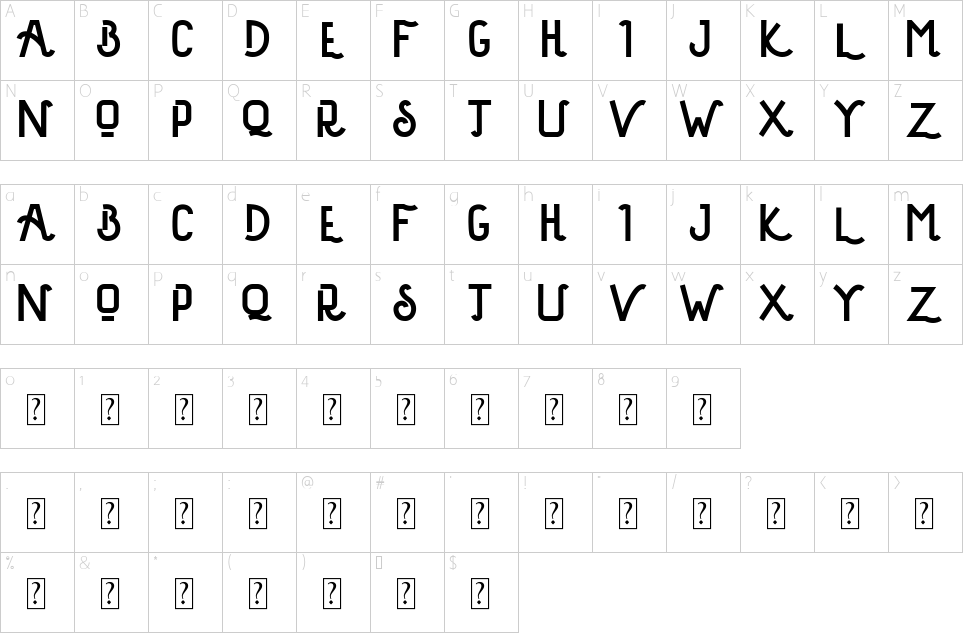
Millions Font é uma elegante e versátil fonte gráfica gratuita disponível para Windows e Mac. Desenvolvida por nirmalagraphics, esta fonte combina elementos minimalistas e modernos que se adaptam perfeitamente a uma ampla variedade de aplicativos e projetos. Com seu design cuidadosamente pensado, a fonte é ideal para criar textos profissionais e sofisticados em qualquer aplicativo de edição de texto. Desde a criação da fonte, mais de 6.464 pessoas já baixaram milhões de fontes gratuitas, o que reforça a sua popularidade e qualidade. Este é um excelente recurso para designers, especialistas em design gráfico e qualquer pessoa que busca uma fonte gráfica limpa e resistente para seus projetos.